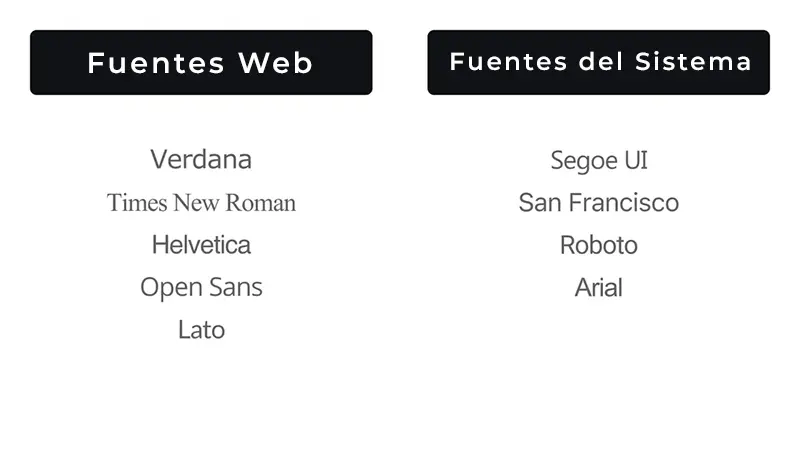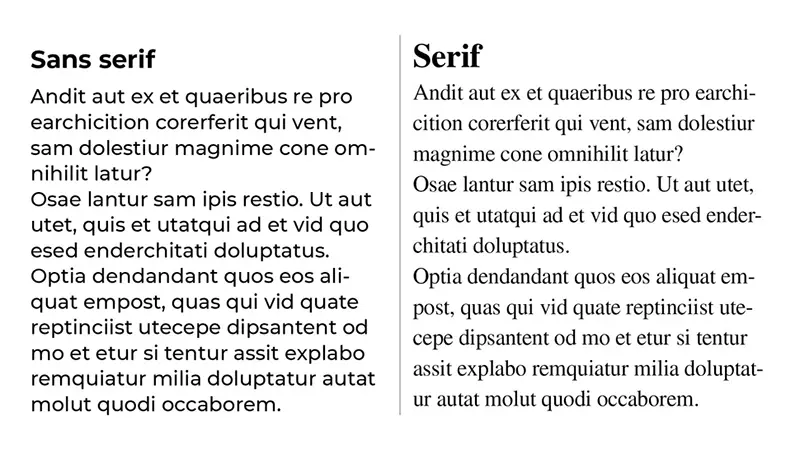
En este articulo te explicamos el papel de los tipos de letra en la configuración de la percepción de una marca y el trío tipográfico que garantiza una buena experiencia de usuario.
La tipografía es mucho más que simplemente elegir una fuente: juega un papel fundamental en la configuración de la identidad de una marca e influye en la experiencia del usuario en el mundo digital. Desde el momento en que un visitante ingresa a un sitio web o abre una aplicación, la tipografía ayuda a establecer el tono, transmitir personalidad y guiar a los usuarios a través del contenido sin problemas.
Los tipos de letra adecuados no solo mejoran la legibilidad, sino que también contribuyen al reconocimiento de la marca, el compromiso emocional y la usabilidad general.
En este artículo, exploramos el papel crucial de la tipografía en el branding y el diseño digital. Explicaremos por qué la tipografía es un elemento clave para el reconocimiento de marca, cómo ciertas tipografías pueden influir en la percepción y el impacto de la buena (o mala) elección de fuentes en la credibilidad y la confianza del usuario.
Además, brindaremos información sobre cómo seleccionar tipografías para plataformas digitales, considerando factores como la legibilidad, la compatibilidad con diferentes dispositivos y el equilibrio entre estética y rendimiento.
La tipografía es un elemento fundamental de la comunicación visual, y en la era digital, su papel en la percepción de la marca es más crucial que nunca. Elegir las tipografías adecuadas para un sitio web o aplicación puede influir significativamente en la percepción de una marca por parte de los usuarios, influyendo en todos los aspectos, desde la legibilidad y la legibilidad hasta las asociaciones emocionales y el reconocimiento de marca.
Por qué la tipografía es importante para el reconocimiento de una marca
Al igual que un logotipo o una paleta de colores, una tipografía puede convertirse en un poderoso activo de marca. Una tipografía distintiva y bien elegida puede:
Transmitir personalidad de marca: una fuente cursiva divertida podría ser adecuada para una marca infantil, mientras que una fuente sans-serif audaz podría transmitir fuerza y modernidad para una empresa de tecnología.
Mejorar el reconocimiento de una marca: el uso constante de un tipo de letra específico en todas las plataformas crea una identidad de marca cohesiva, lo que hace que la marca sea reconocible al instante.
Aumentar la confianza y la credibilidad: una tipografía profesional y bien elaborada mejora la percepción de confiabilidad y credibilidad de una marca.
Una tipografía mal elegida puede dañar significativamente la imagen de una marca en el mundo digital. Puede hacer que una marca parezca poco profesional, anticuada o incluso poco fiable. Si una tipografía es difícil de leer, puede frustrar a los usuarios y ahuyentarlos. El uso inconsistente de las tipografías también puede confundir a los usuarios y diluir el reconocimiento de la marca.
En última instancia, una mala tipografía puede afectar negativamente la credibilidad de una marca, la experiencia del usuario y el éxito general en un entorno digital.
Elegir tipografías para el mundo digital
Los diseñadores se enfrentan a retos únicos al seleccionar tipografías para medios en pantalla. A continuación, se presentan algunas consideraciones clave:
Legibilidad: Prioriza las tipografías fáciles de leer en diferentes tamaños y resoluciones de pantalla. Factores como la altura de la x, el kerning y la altura de línea contribuyen a una legibilidad óptima.
Representación de fuentes: Los distintos sistemas operativos y navegadores representan las fuentes de forma distinta. Prueba las tipografías que eljas en diferentes plataformas para garantizar una visualización uniforme.
Fuentes web vs. fuentes del sistema: Las fuentes web ofrecen mayor flexibilidad de diseño, pero pueden afectar los tiempos de carga de las páginas. Las fuentes del sistema vienen preinstaladas en los dispositivos del usuario, lo que garantiza una carga más rápida, pero limita las opciones de diseño.
Ejemplos de Fuentes Web (Google Fonts, etc.):
- Roboto: Muy popular en sitios web y apps. Moderna y legible.
- Open Sans: Súper clara y versátil. Ideal para párrafos y UI.
- Lato: Estética limpia con un toque amigable.
- Montserrat: Estilo geométrico. Excelente para títulos llamativos.
- Merriweather: Serif elegante, perfecta para blogs y artículos largos.
Ejemplos de Fuentes del Sistema (instaladas por defecto):
- Arial: Una de las más comunes en Windows y Mac.
- Times New Roman: Clásica fuente serif. Muy usada en documentos formales.
- Calibri: Fuente por defecto en versiones recientes de Microsoft Word.
- Courier New: Monoespaciada. Común en código y documentos técnicos.
- Georgia: Serif elegante y legible en pantallas.
Jerarquía y flujo visual: utiliza diferentes tamaños, pesos y estilos de fuente para crear una jerarquía visual clara y guiar la mirada del usuario a través del contenido.
Contraste de color: asegúrate de que haya suficiente contraste entre el texto y los colores de fondo para usuarios con baja visión.
Tipografía emocional
Diferentes tipos de letra evocan diferentes emociones y asociaciones:
Fuentes serif: a menudo asociadas con la tradición, la sofisticación y la autoridad.
Fuentes sans-serif: transmiten modernidad, limpieza y simplicidad.
Fuentes de escritura: pueden evocar elegancia, creatividad o alegría.